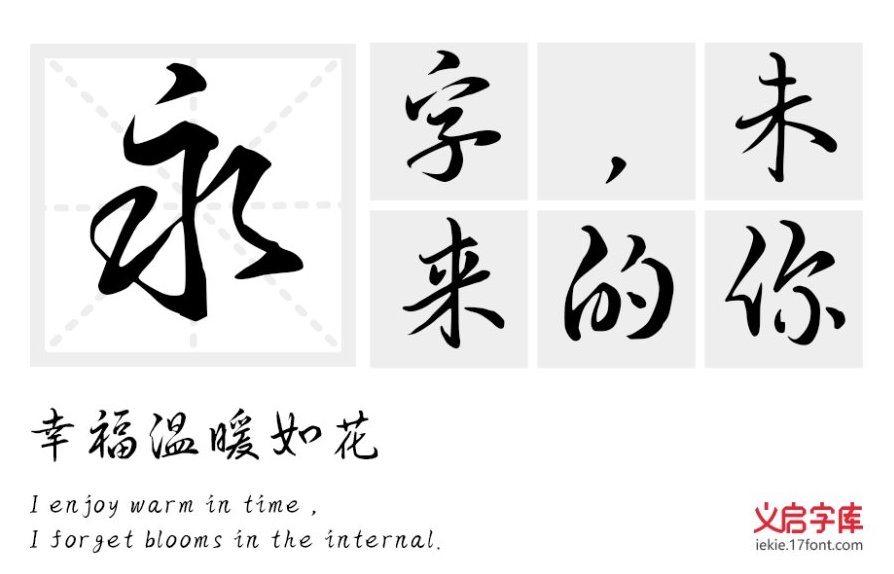
这款字体的名字叫做“一纸情书”。从名字就体现出了这款字体的浪漫主义,这款字体的灵感来源于一句爱的表达“世界再大再繁华,都抵不过你一句:我爱你”。字体结构上保留了端庄文章感,在创新上加入了抑扬顿挫感十分新颖,比较适合面积的去使用作为标题等,让人耳目一新。
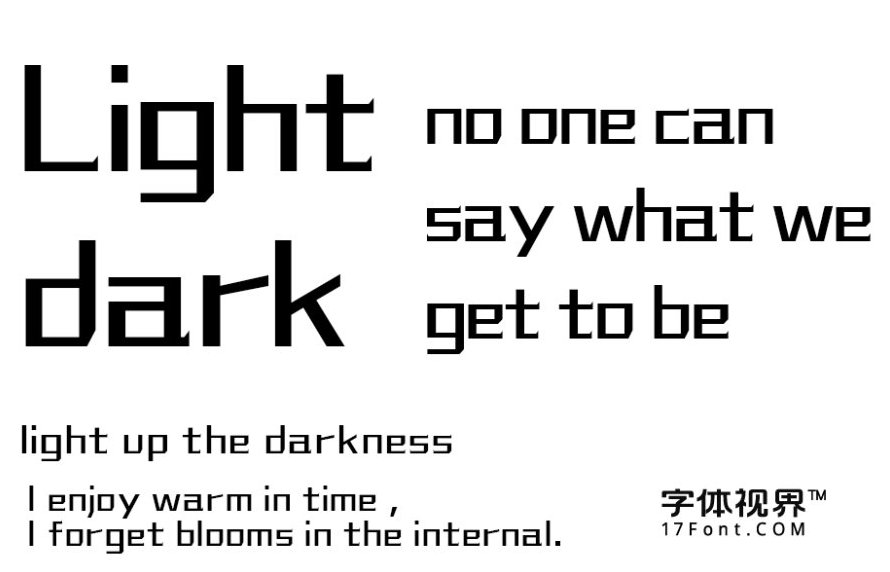
这是一款英文字体,“Witarna” 这款字体笔画以直线和对角线构成,彰显出力量感。字迹清晰便于字体识别 ,笔画张弛有度。辨识度高、观赏性十足,浪漫又不正式感。用于屏幕显示和包装设计、印刷都非常合适。